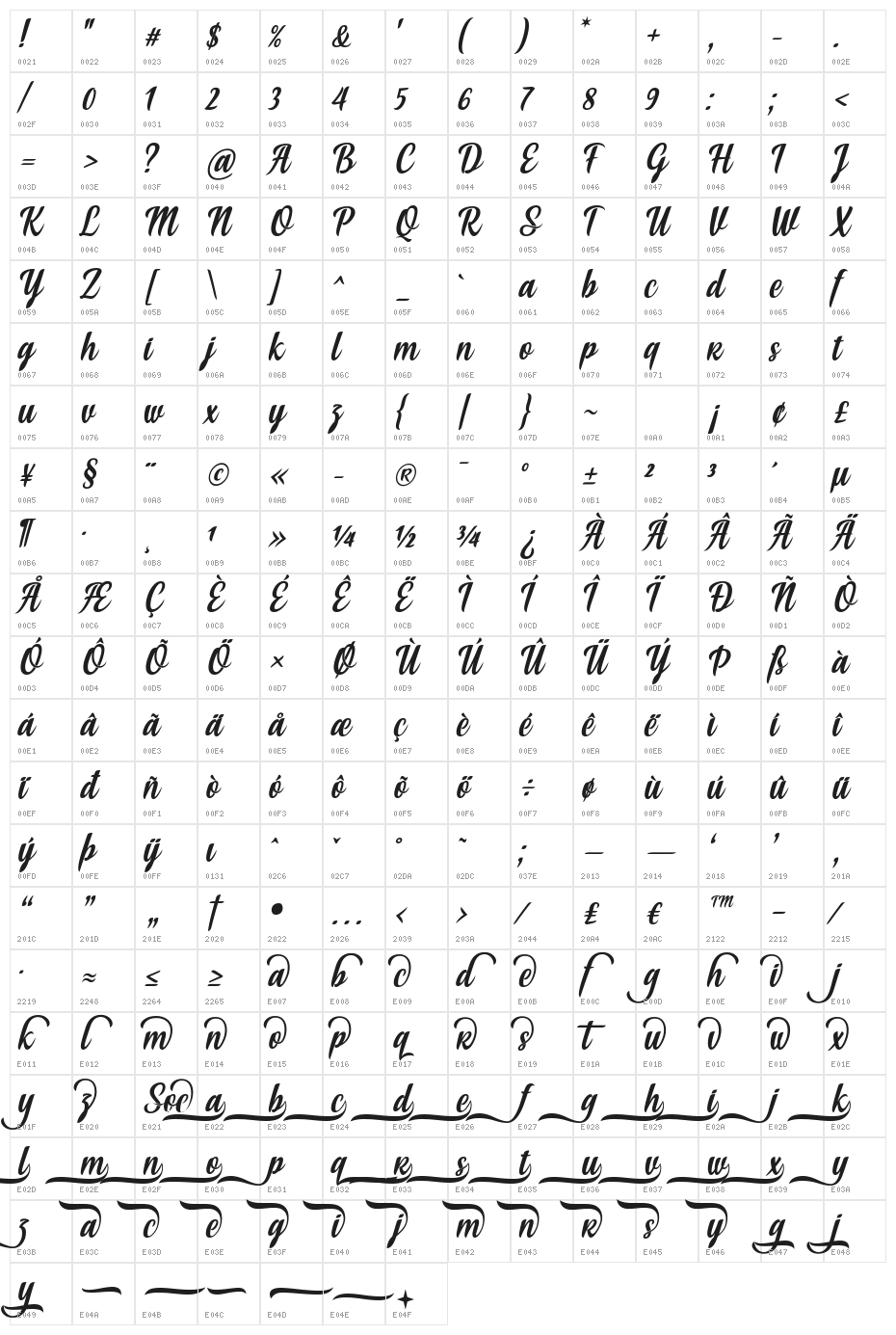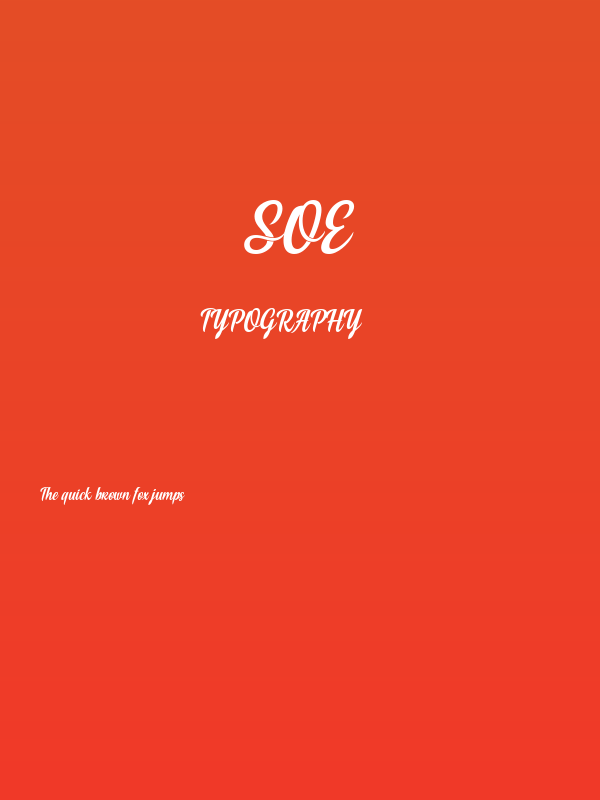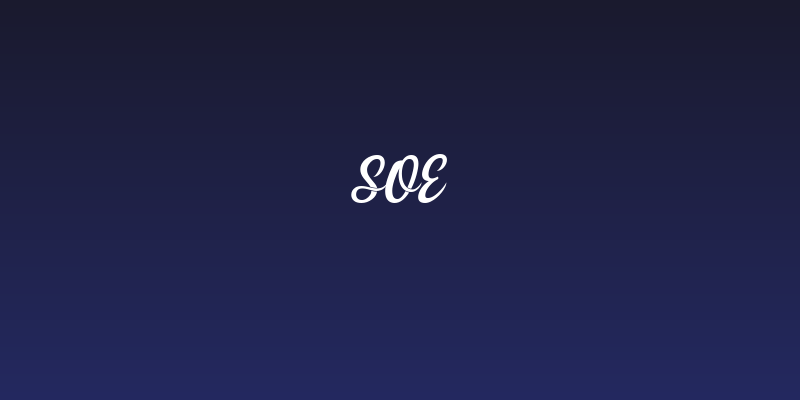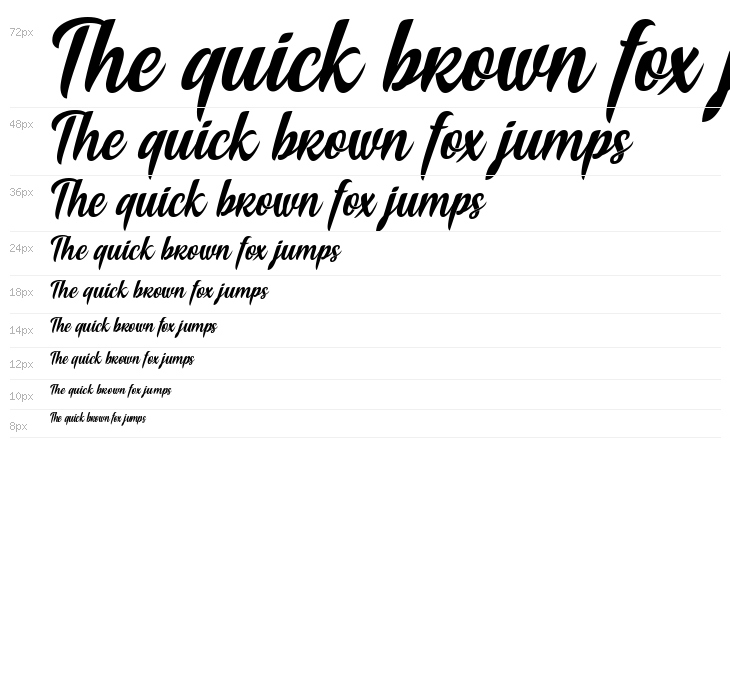
Soe Font
| Stile generale | Elegant, Decorative |
| Caso d'uso | Logos, Headlines, Invitations |
| Progetti proposti | Ideal for wedding invitations, branding, logos, and elegant packaging design. |